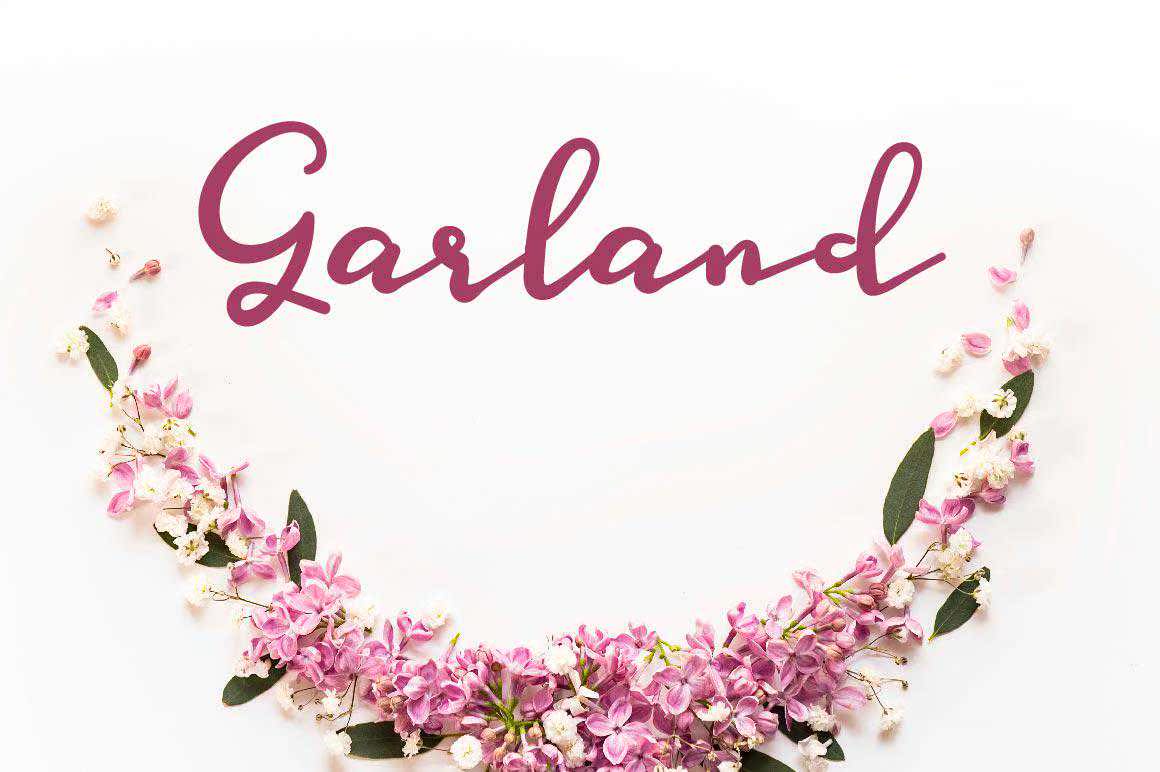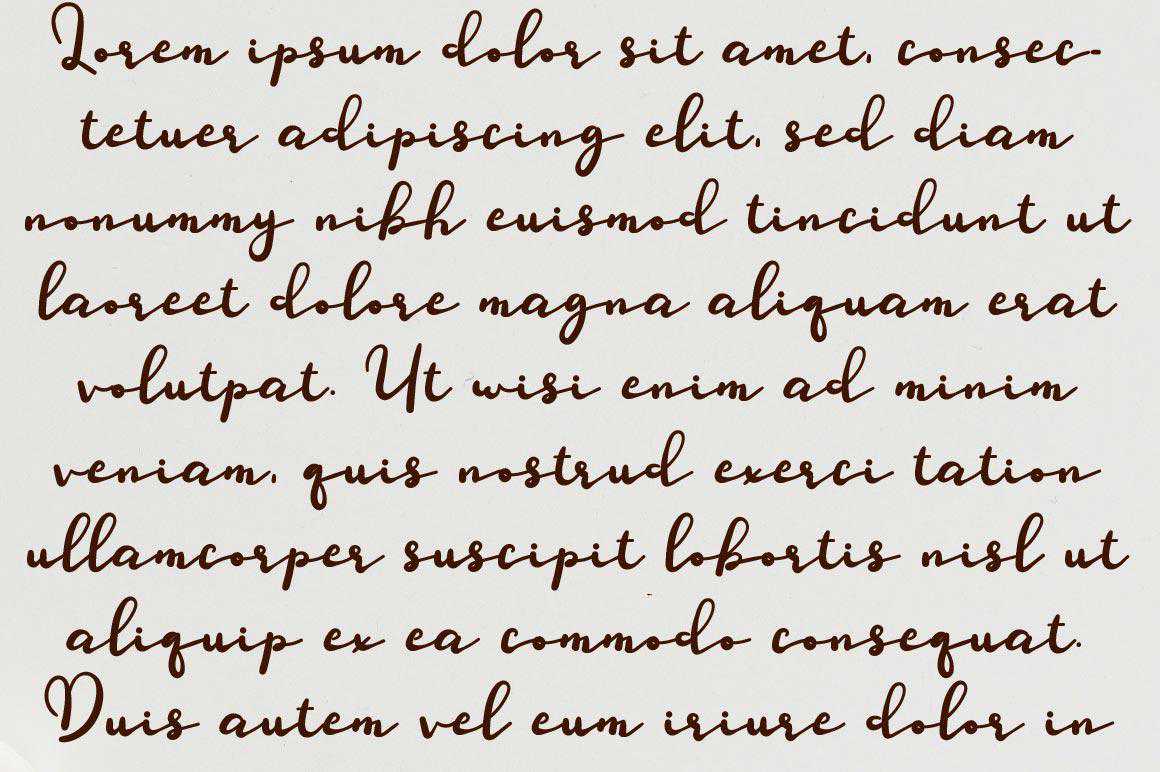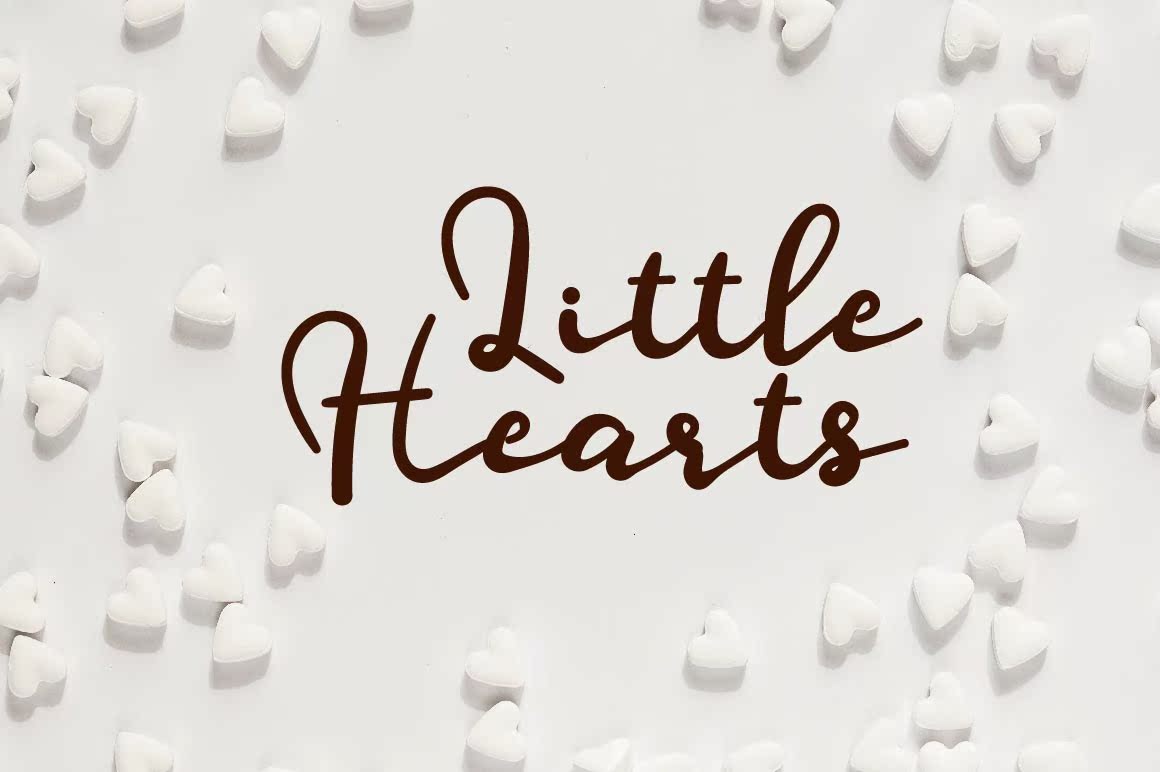
DistribleryScriptFont是一种装饰性的脚本字体,可以在许多地方使用。字体经过精心设计,使您的文本看起来很漂亮。使用现代样式,此字体可以完美地形成任何不同的项目Ex:引用、博客标题、海报、婚礼、品牌、徽标、时尚、服装、信函、邀请函、文具、,等等。DefilerScriptFont是一种装饰性的脚本字体,可以在许多地方使用。字体经过精心设计,使您的文本看起来很漂亮。使用现代风格,此字体可以完美地形成任何不同的项目:引用、博客标题、海报、婚礼、品牌、标志、时尚、服装、信件、邀请函、文具等。